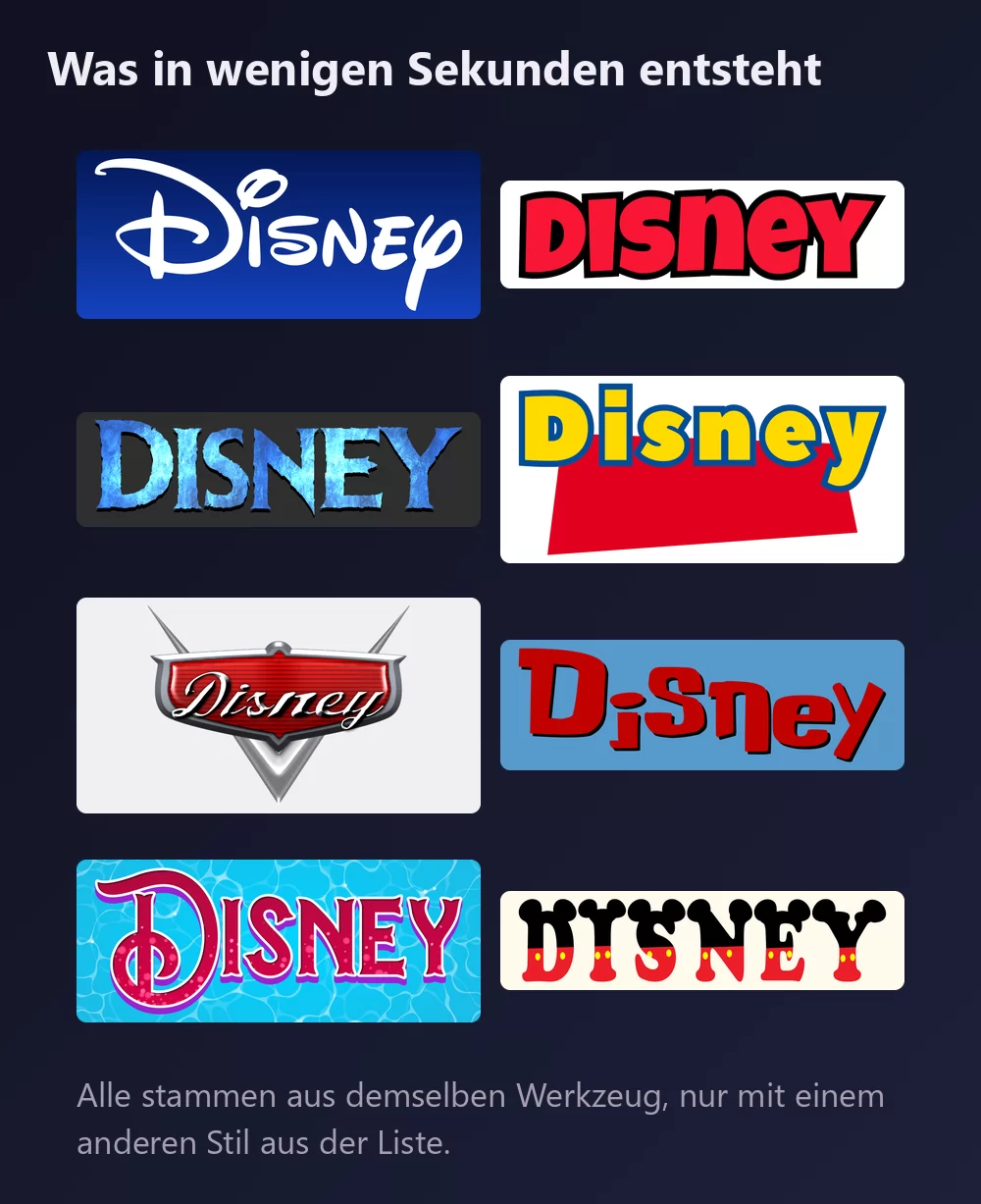
Alle stammen aus demselben Disney-Schriftgenerator, nur mit einem anderen Stil aus der Liste. Nichts zu installieren, kein Konto.
Über die Disney-Schrift
The Walt Disney Company wurde 1923 von den Brüdern Walt und Roy O. Disney gegründet und ist zu einem der größten Medienkonzerne der Welt geworden. Micky Maus, die bekannteste Figur, ist das offizielle Maskottchen.
Der Schriftzug im Logo ist eine stilisierte Version von Walt Disneys Unterschrift. Er dient seit 1956 als Firmenlogo und wurde nie als Schrift veröffentlicht: Es gibt keine offizielle Datei zum Installieren. Die Schrift, die stattdessen alle herunterladen, ist Waltograph, von Justin Callaghan nach dem Logotyp gezeichnet. Sie gibt es in zwei Varianten: Waltograph 42 mit Groß- und Kleinbuchstaben sowie einigen Ligaturen und Alternativformen, und Waltograph UI, ein Unicase-Schnitt, der in kleinen Größen und auf Bildschirmen lesbar bleibt. Beide sind für den privaten Gebrauch kostenlos.
Öffne den Generator und ersetze den Beispieltext durch deinen eigenen: den Namen eines Kindes, einen Partytitel, einen Familiennamen für das Reise-Shirt. Die Buchstaben werden beim Tippen neu gezeichnet. Bleib bei Groß- und Kleinschreibung: Der Signaturstil ist eine Schreibschrift, und ein Wort in Versalien verliert das hohe, geschwungene D, an dem man Disney erkennt.
Der Klassiker ist die weiße Signaturschrift auf einem königsblauen Verlauf. Im Tab Stile lassen sich Füllung, Kontur und Schatten getrennt ändern, du behältst also die Buchstabenformen und nimmst die Farben woandershin: Gold auf Marineblau für eine Hochzeit, Rosa für eine Prinzessinnenparty.
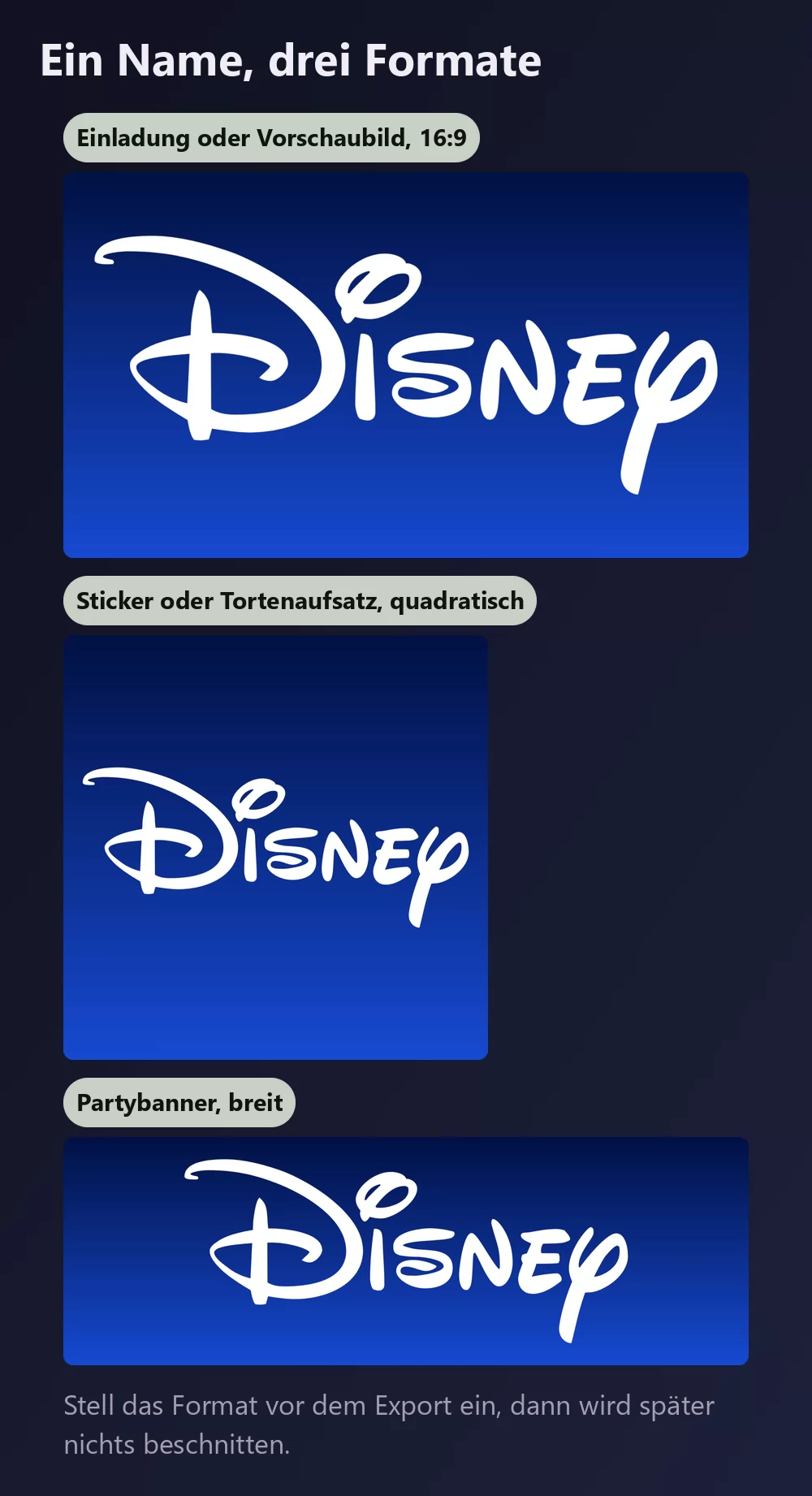
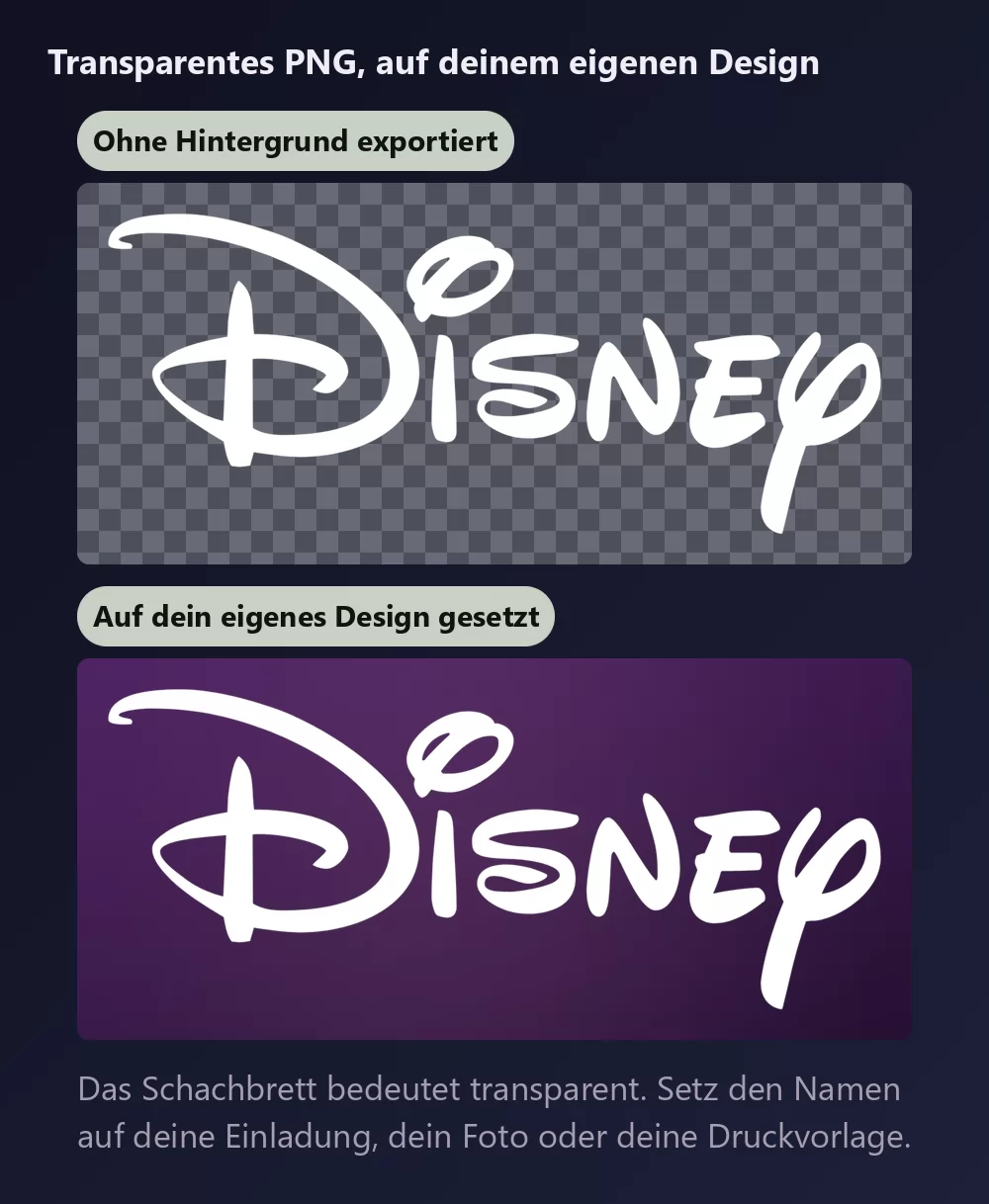
Lange Namen füllen die Breite schnell
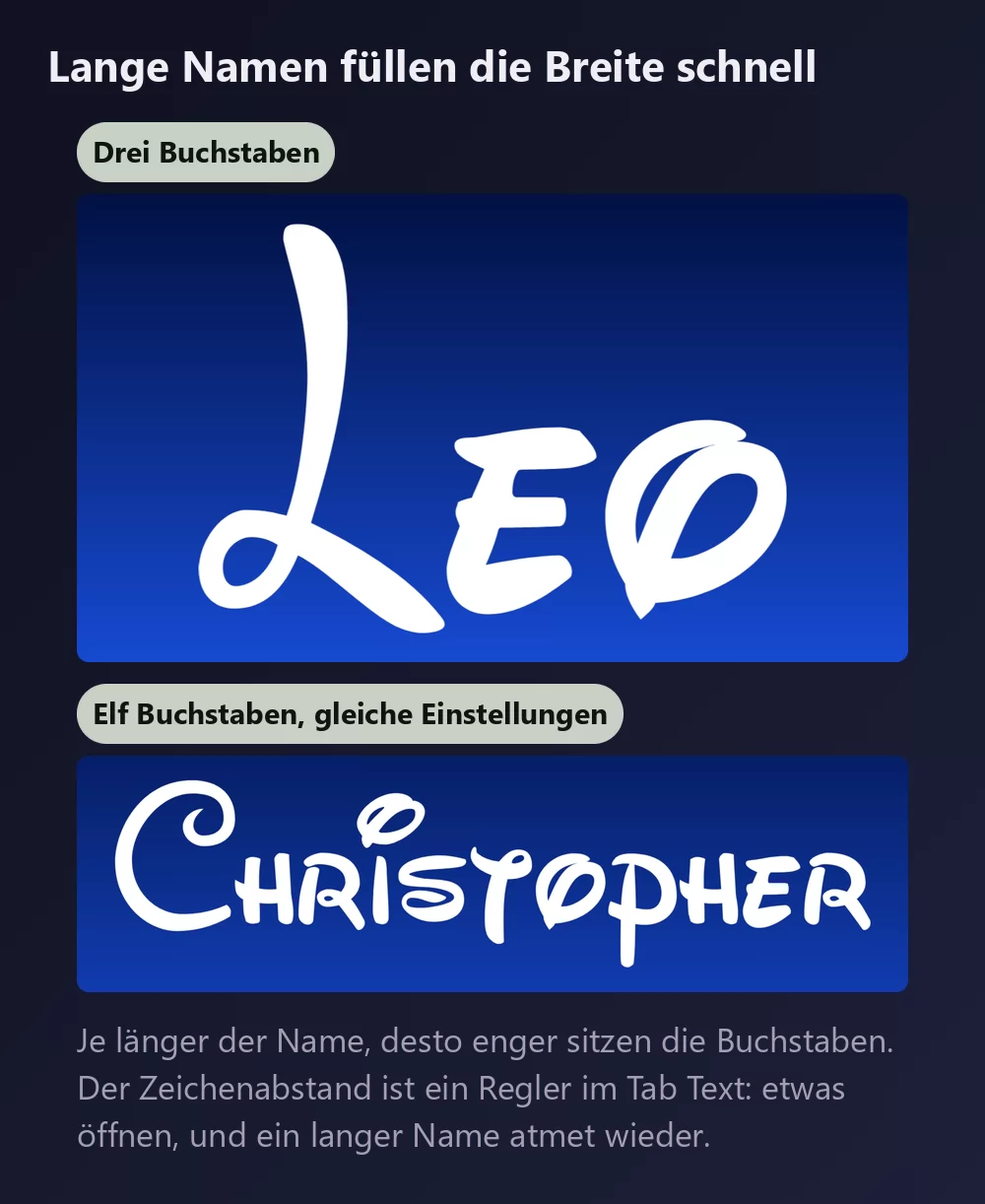
Je mehr Buchstaben, desto enger sitzen sie. Der Zeichenabstand ist ein Regler im Tab Text: etwas öffnen, und ein langer Name wirkt nicht mehr gequetscht. Derselbe Tab enthält Zoom, Zeilenhöhe, Bogen und Drehung.
Der Signatur-Look oder der Micky-Look
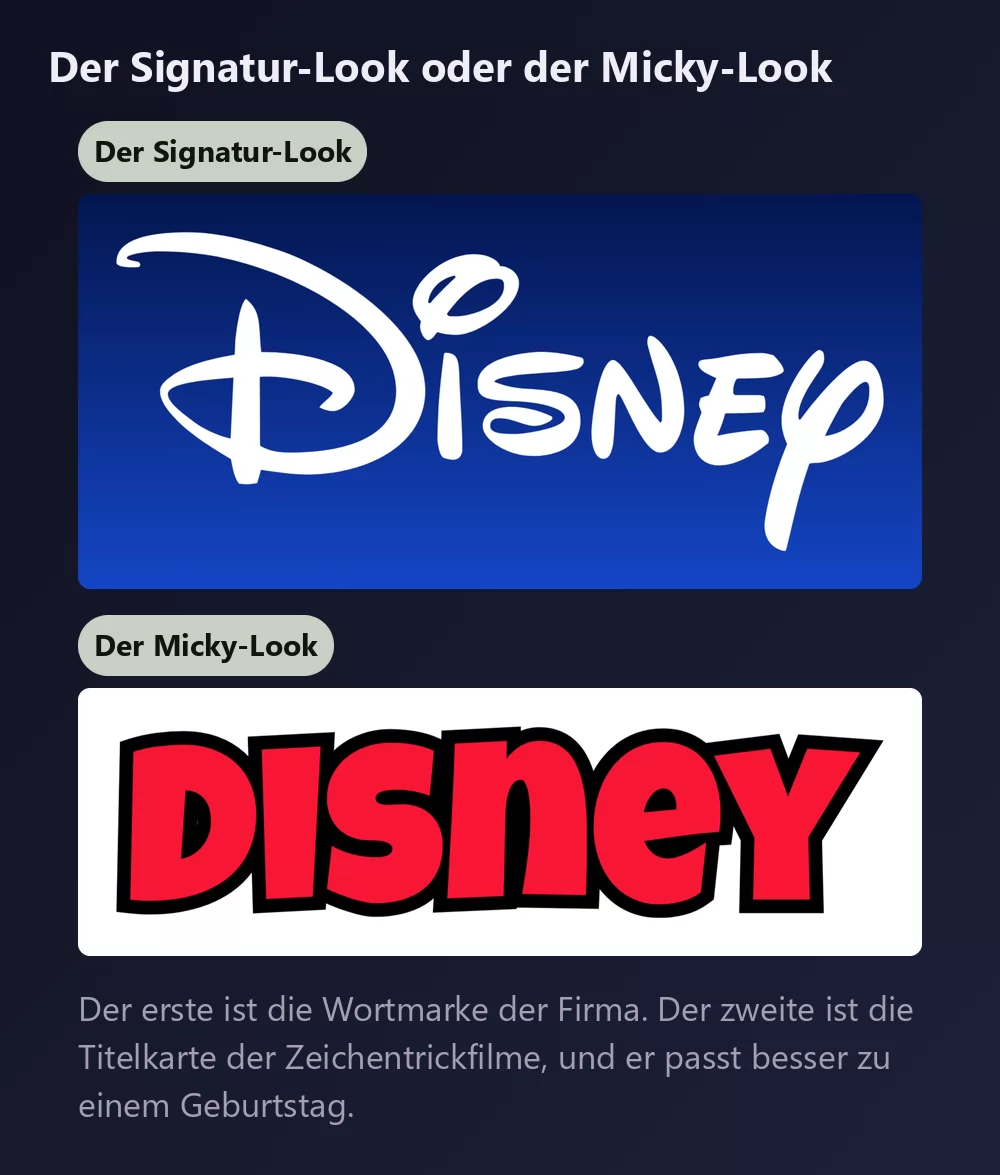
Der Signatur-Look ist die Wortmarke der Firma: eine fließende Schreibschrift mit dem hohen, geschwungenen D, weiß auf Blau. Das haben die meisten im Kopf, wenn sie „die Disney-Schrift" sagen.
Der Micky-Look ist die Titelkarte der Zeichentrickfilme: fette rote Versalien mit schwarzer Kontur, die Schrift der Micky-Maus-Kurzfilme. Er trägt kein Firmenbranding, ist quer durch den Raum lesbar, und für einen ersten Geburtstag funktioniert er meist besser als die Signatur. Der Micky-Maus-Schriftgenerator hat ihn als Voreinstellung.
Welche Schrift, wenn du eine installieren willst
Das Logo selbst ist keine Schrift. Es ist ein eigens gezeichneter Schriftzug, also ist jede Datei namens „Disney-Schrift" jemandes Nachbildung davon.
New Waltograph von 538Fonts ist eine überarbeitete Version auf FontSpace, wo sie die meistgeladene Schrift im Disney-Stil ist. FontSpace führt sie als 100 % kostenlos, was dort die kommerzielle Nutzung einschließt. Lies die Readme im Download, bevor du dich für einen Kundenauftrag darauf verlässt.
Mouse Memoirs von Astigmatic ist die richtige Wahl, wenn die Lizenz sauber sein muss. Sie liegt seit 2012 unter der Open Font License auf Google Fonts und ist damit frei für kommerzielle Arbeit. Sie ist keine Kopie der Signatur: eine hohe, handgeletterte Grotesk im Geist der frühen Cartoons, die auf einem Poster oder einer Speisekarte gut zum Signaturstil passt.
Disney-Schriften nach Film und Figur
Das Firmenlogo ist das eine. Jeder Film hat seinen eigenen Titelschriftzug, und die meisten Suchergebnisse zu „Disney-Schrift" sind in Wahrheit Listen davon. Derselbe Generator hat für die meisten einen Stil, jeder auf seiner eigenen Seite:
- Micky-Maus-Schrift : fette rote Versalien mit schwarzer Kontur
- Minnie-Maus-Schrift : rosa Punkte und eine Schleife auf jedem Buchstaben
- Frozen-Schrift : eisblaue Versalien mit Reif an den Kanten